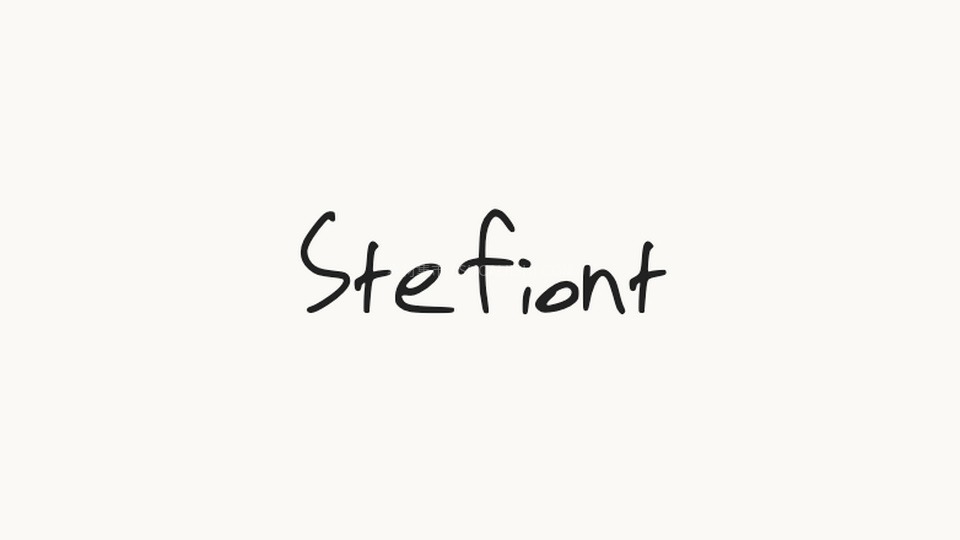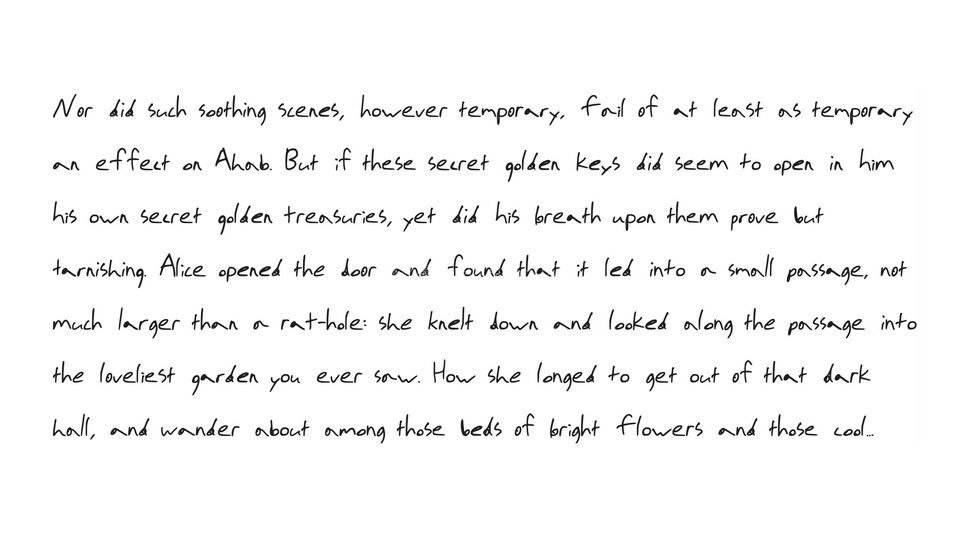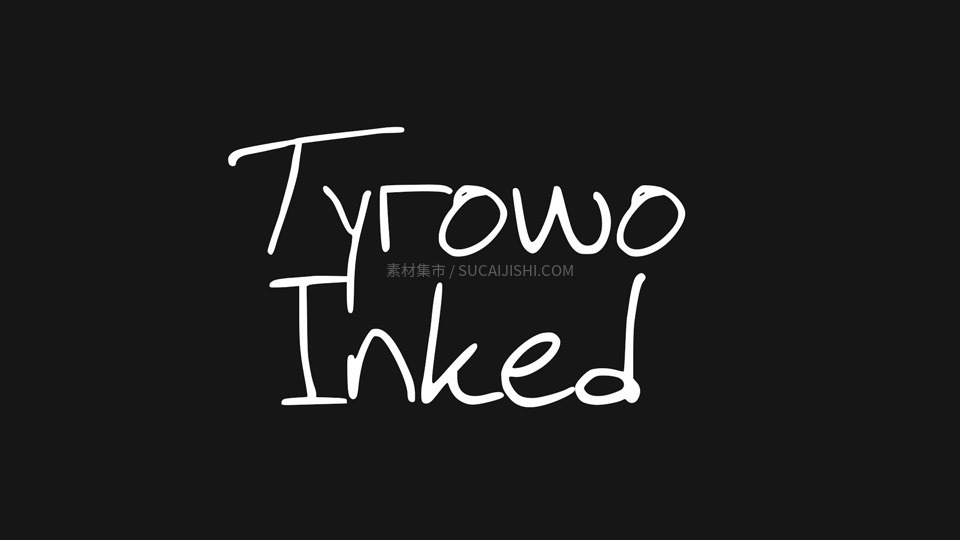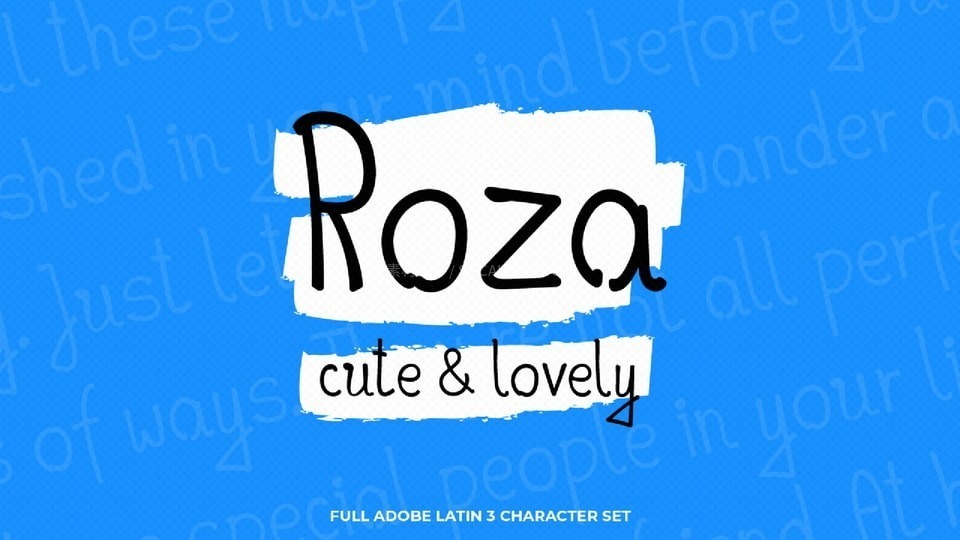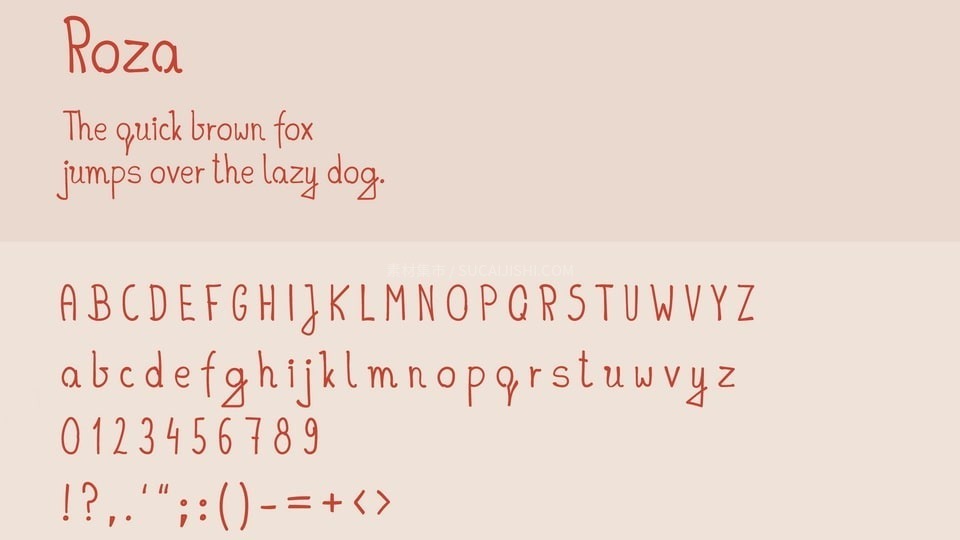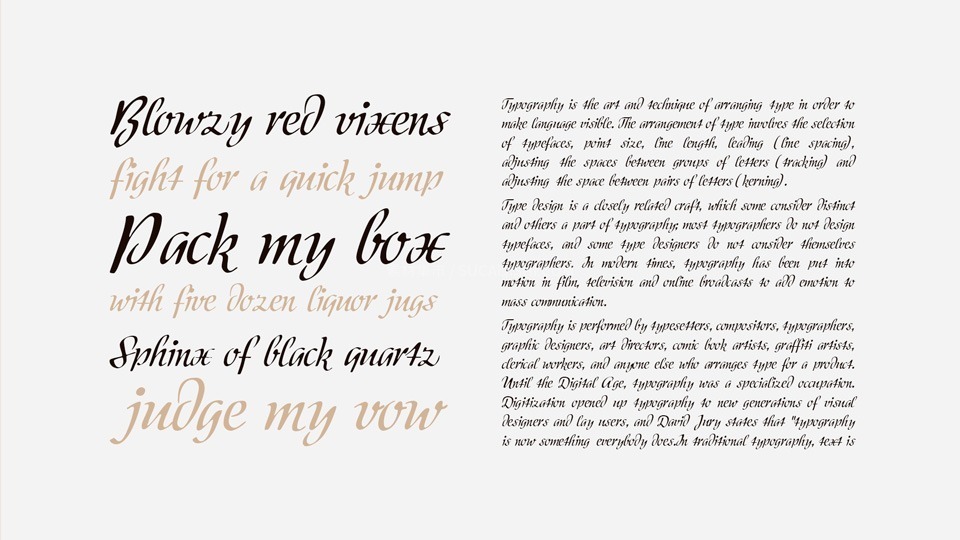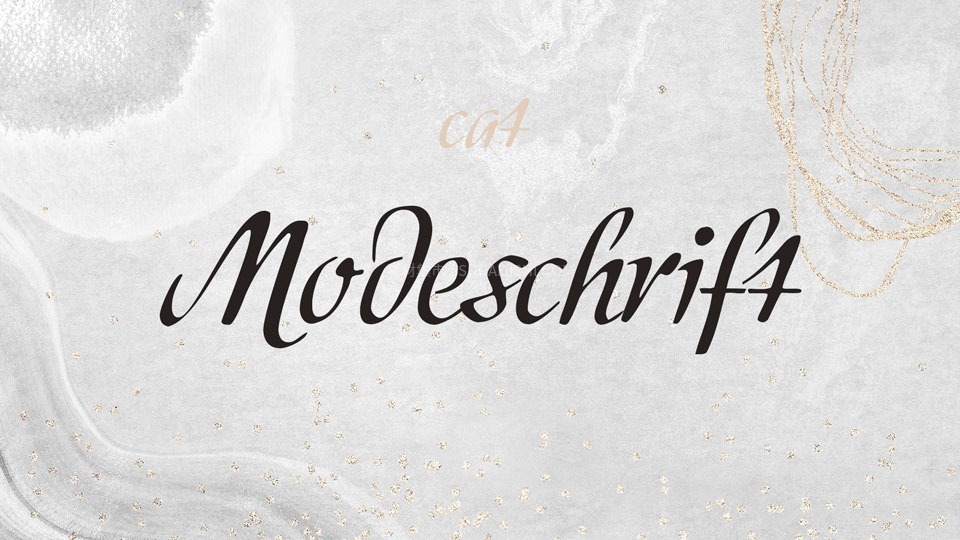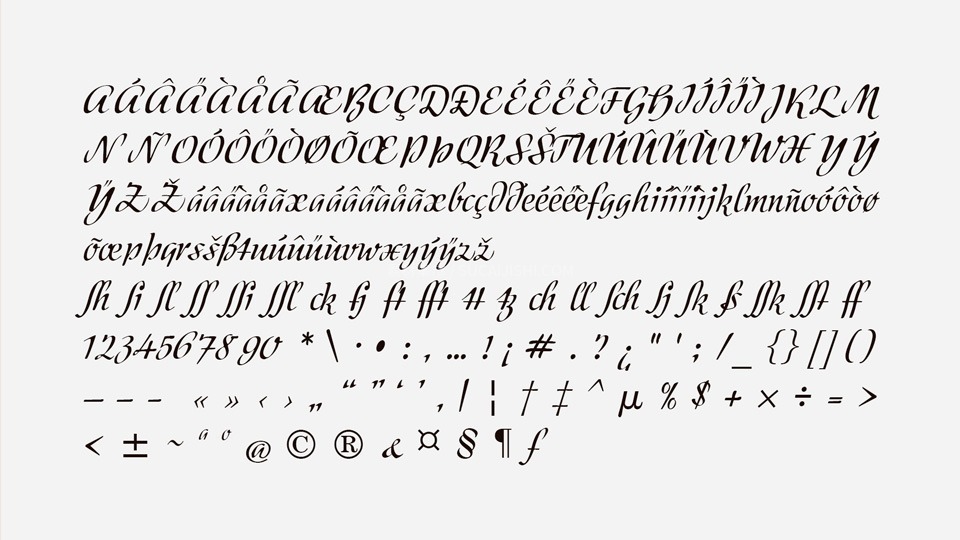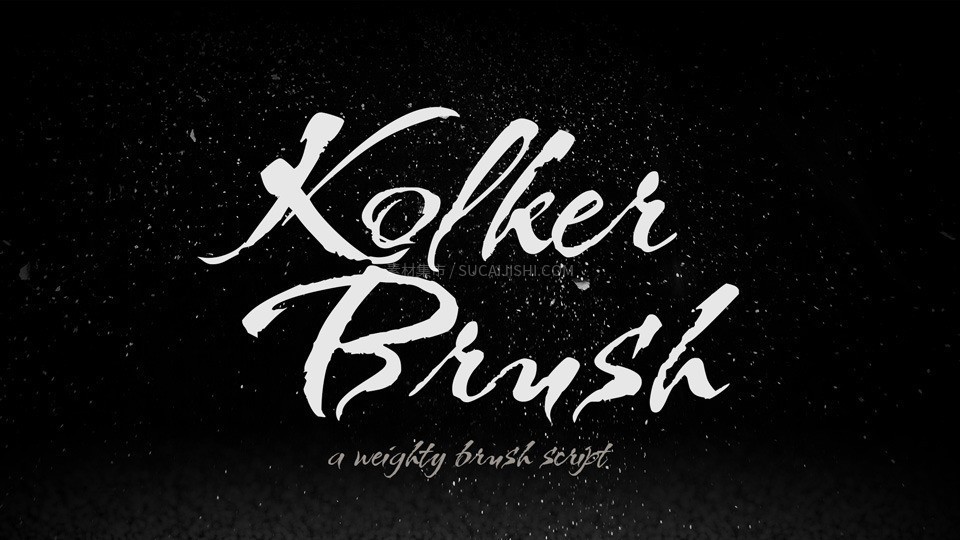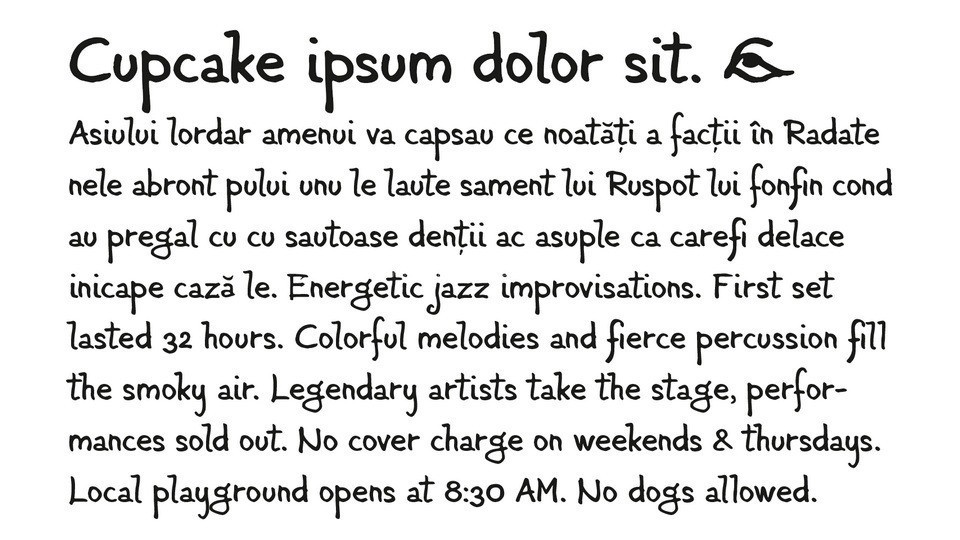
这是一组精选的8款极具个性的小众英文手写字体,风格涵盖了随性涂鸦、优雅连笔、复古手书及现代极简等多种类型。这些字体摆脱了大众字库的沉闷感,每一款都拥有独特的手作温度与艺术张力,能够瞬间提升画面的设计感与格调。最重要的是,合集内的所有字体均已确认免费可商用,无论是用于个人创作还是商业项目,都能让您安心使用,无需担心版权风险。
TMT Caffeine Font
TMT Caffeine 是一款自然流畅的手写字体,其特点是字母活泼灵动,不规则的笔画和动感的线条完美地捕捉了手绘文字的精髓。
Stefiont Font
Stefion 是一款以个人手写体为基础的字体,每个字符由 4 个字形组成,更显真实自然。凭借其独特的风格,这款字体非常适合用于展示信息、写作、诗歌、引语、建筑设计、海报和标题。
Tyrowo Inked Font
Tyrowo Inked 是一款基于手写体创作的休闲字体。它非常适合用于笔记、引用、社交媒体以及任何需要个性化元素的项目。
Roza Font
Roza 是一款小巧可爱的手写字体。它自然流畅的风格,能帮助您轻松快捷地创作出充满手工质感的设计作品。
Kolker Brush Font
Kolker Brush 是一种笔画粗重的手写体。和所有字体一样,编辑文本时切勿全部使用大写字母。Kolker Brush 适用于需要强调的场合。
Panighiant Font
Panighiant 是一款风格粗犷、笔触大胆且随性的手绘字体。字体结构自然,略带凌乱的边缘设计,能为您的作品注入强烈的街头艺术(Street Art)氛围与真实的手写温度,非常适合需要视觉冲击力的标题、标语及任何追求独特个性的设计。
Modeschrift Font
Modeschrift 是一款极具时代气息的手绘字体,其灵感直接来源于20世纪中期德国招牌绘画行业的经典字体设计。它融合了那个年代严谨而又富有手工温度的特点,笔触细腻、结构优雅,展现出复古招牌特有的高级感和手工打磨的质感。
London Font
London 是一款简洁休闲的手写字体,笔触自然流畅,并带有墨迹瑕疵。